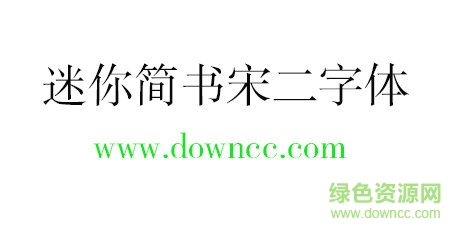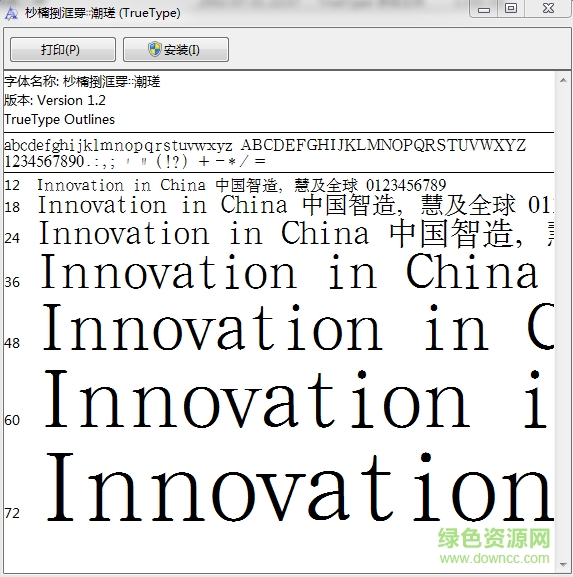
迷你簡(jiǎn)書宋二是一款非常好用的電腦字體,這款字體寫出來(lái)剛勁有力,筆法優(yōu)美,使用范圍也非常廣,大家平時(shí)用來(lái)練字、寫文章也是很不錯(cuò)的,相要利用該字體寫作的朋友可別錯(cuò)過(guò)了這款經(jīng)典之作,歡迎登陸綠色資源網(wǎng)下載使用哦。